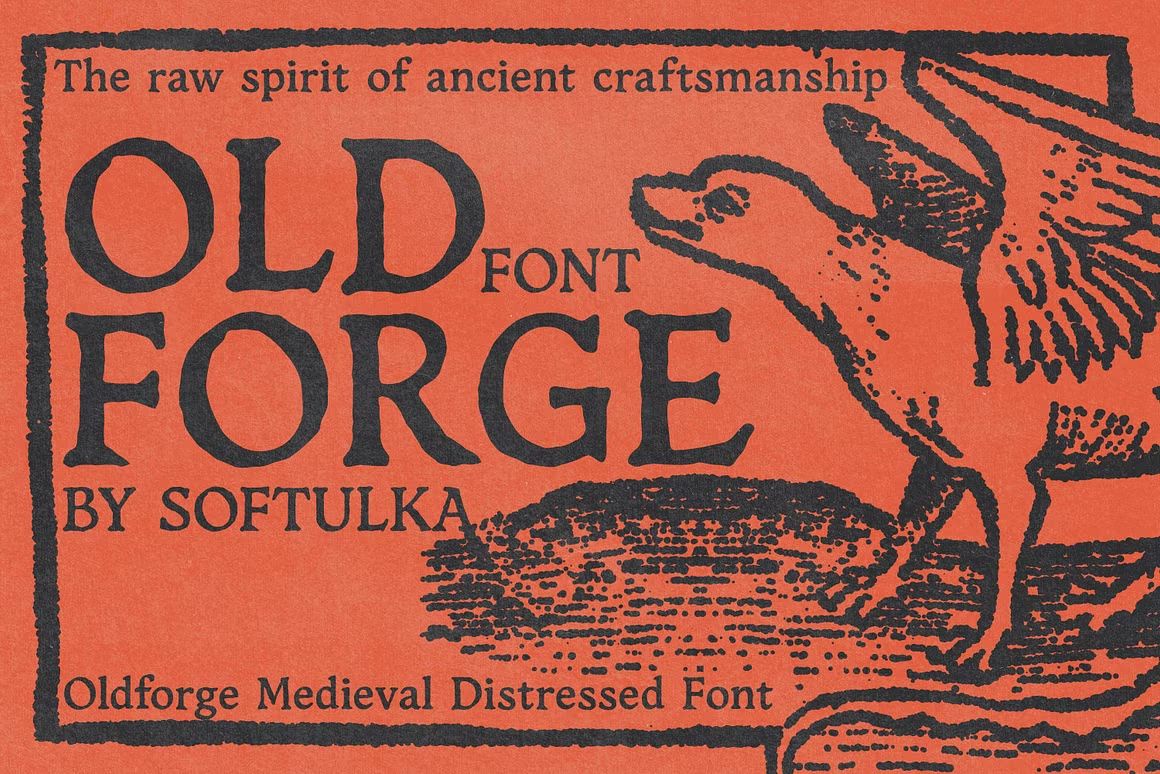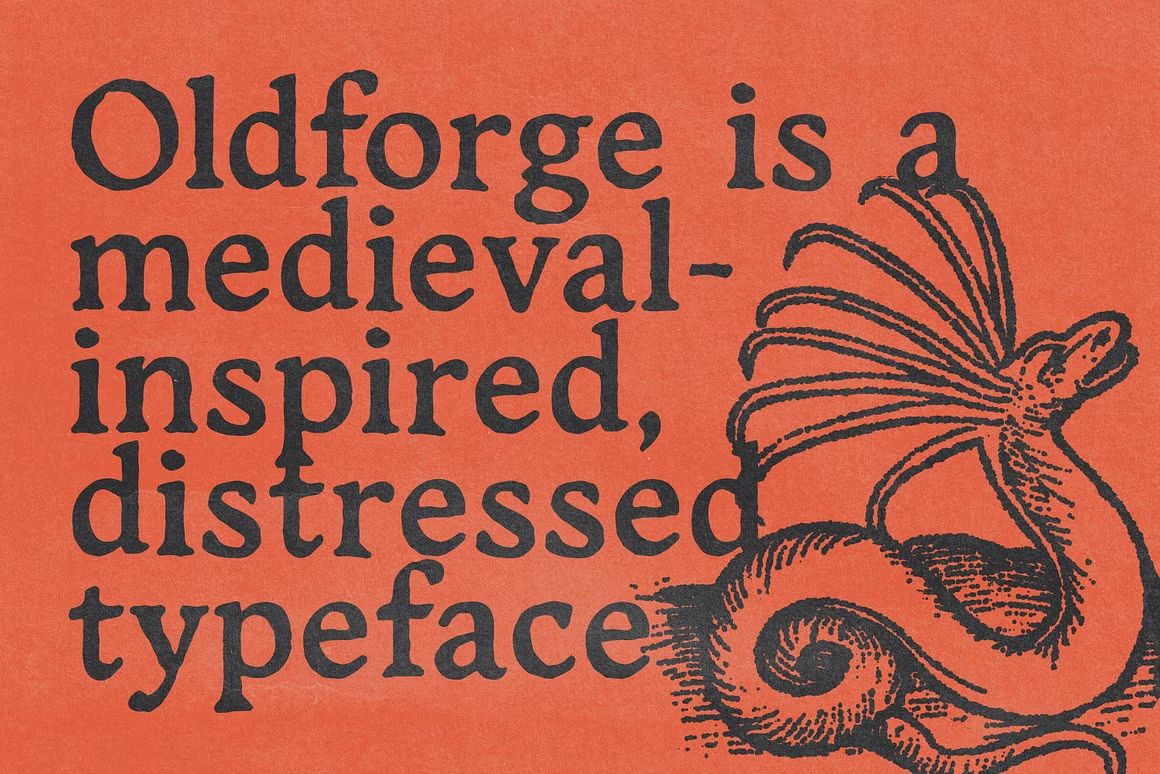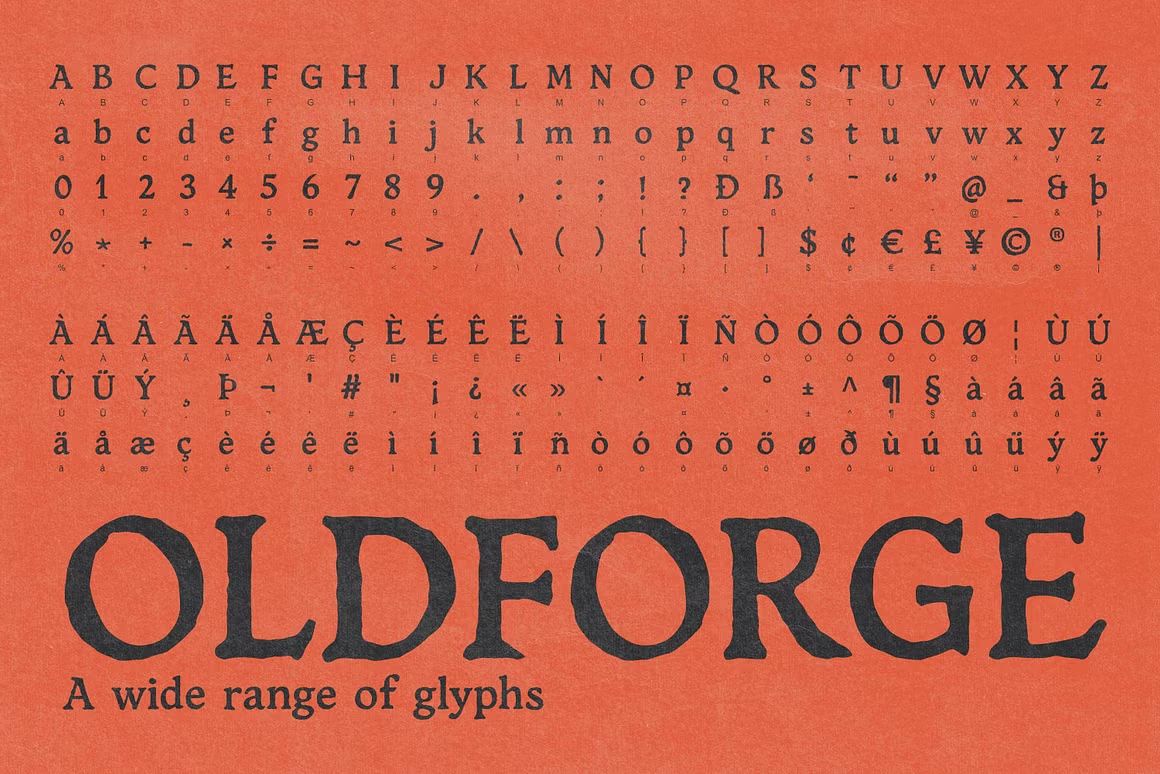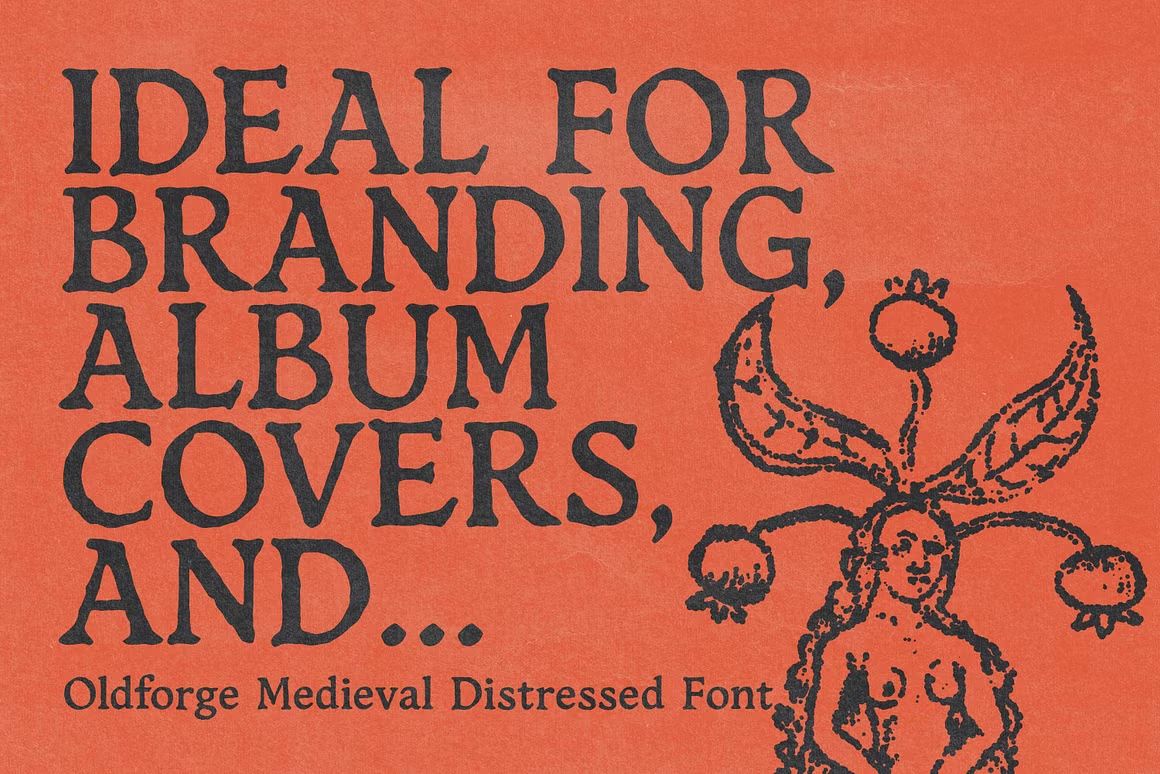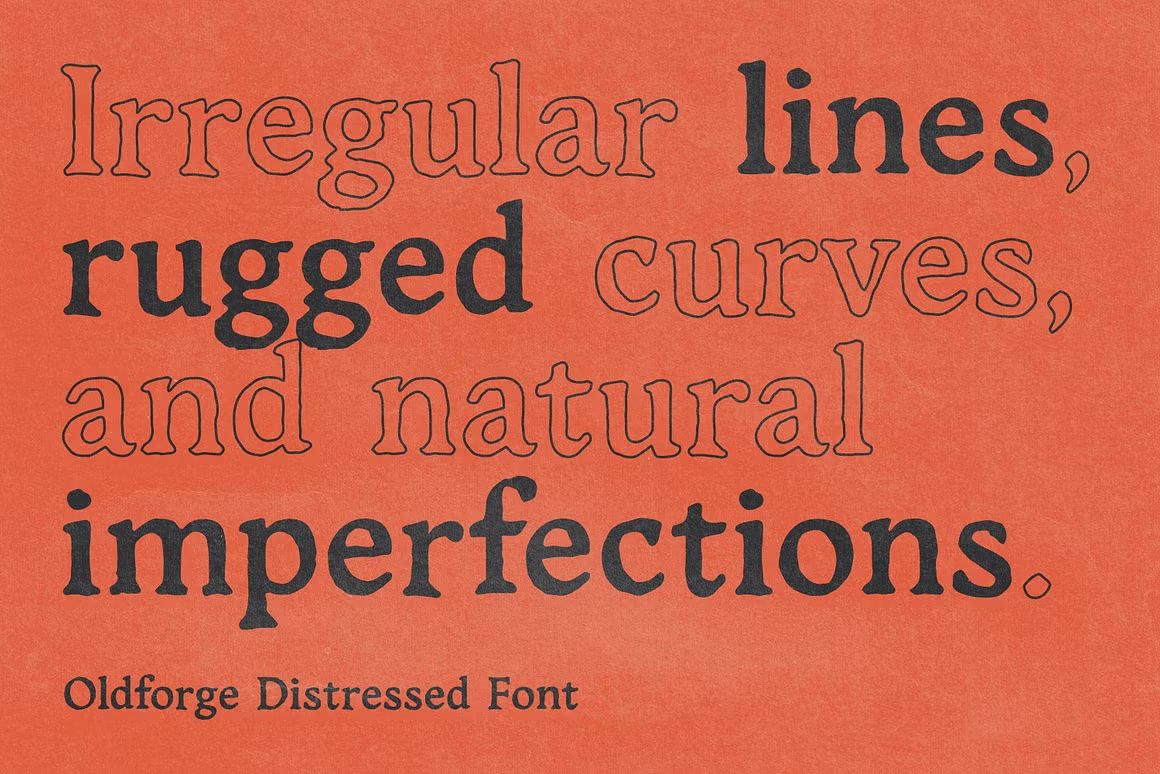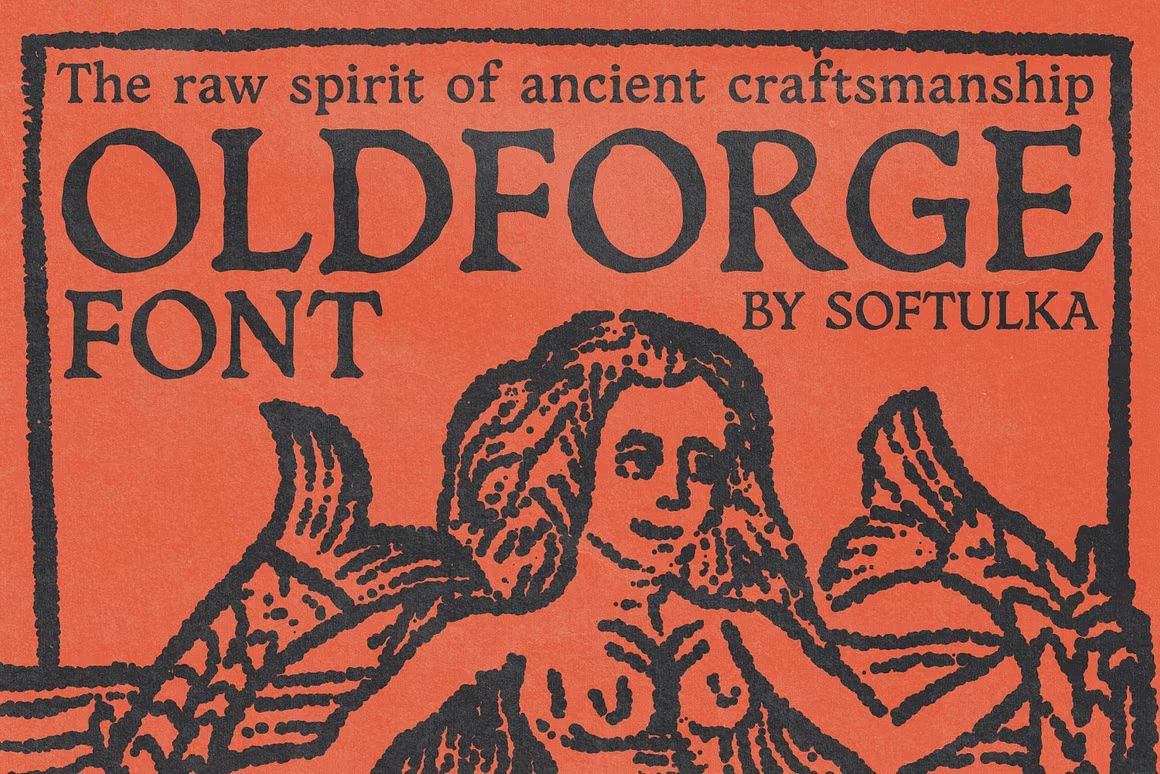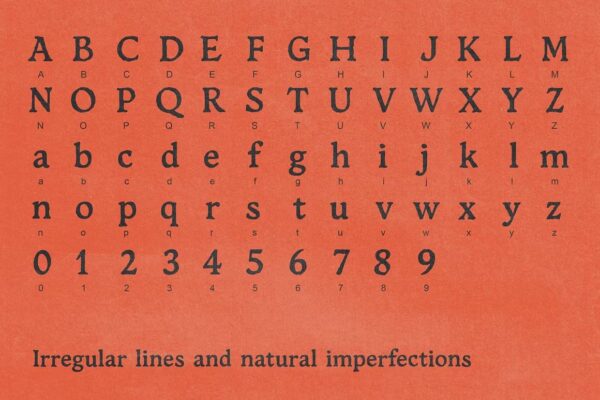
Oldforge – Script Font
Oldforge adalah font script vintage dengan gaya kuas kasar yang berani dan klasik. Cocok untuk logo retro, label, dan desain handmade. Format OTF/TTF/WOFF, siap digunakan.
Oldforge adalah font script bergaya vintage dengan sapuan tinta yang kasar dan ekspresif. Menggabungkan elemen klasik dan tampilan buatan tangan, font ini sangat cocok untuk logo retro, label produk, poster, kemasan, dan desain bertema kerajinan atau industri. Oldforge memberikan kesan autentik, berani, dan penuh karakter dalam setiap komposisi visual.
• Script vintage dengan tekstur kuas yang natural
• Ideal untuk logo klasik, label, dan desain retro
• Termasuk huruf besar, kecil, angka, simbol, dan ligatur